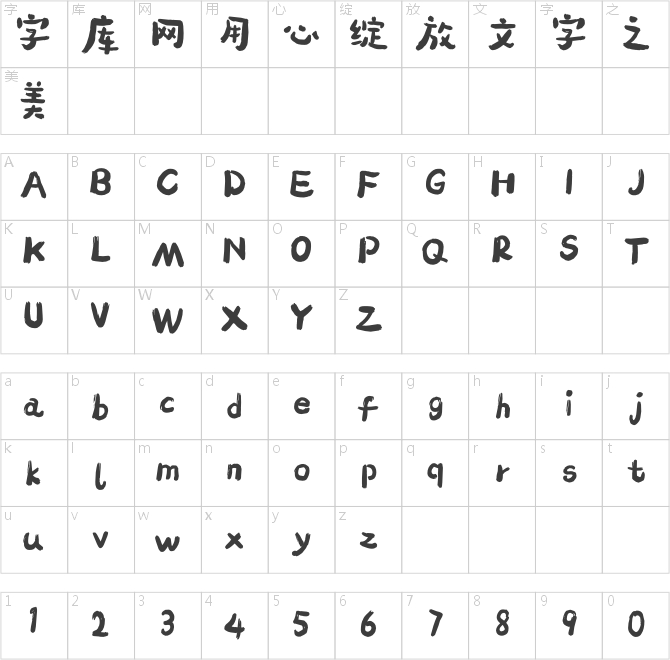
字体名称: 造字工房拙影体
造字工房拙影体,其书风活泼有趣,拙中见巧,字体结构随性自由、风格俏皮可爱,具有很强的视觉感染力,此款字体适用于儿童读物、报刊杂志标题、广告设计等视觉环境,有着极强的应用空间。本字体为简体字库,采用OpenType/CID格式,Adobe-GB1-5编码。基于中华人民共和国GB2312-80字符集标准,另按需添加101个汉字。共收容字数6864CJK汉字,ASCII常用字符100个。